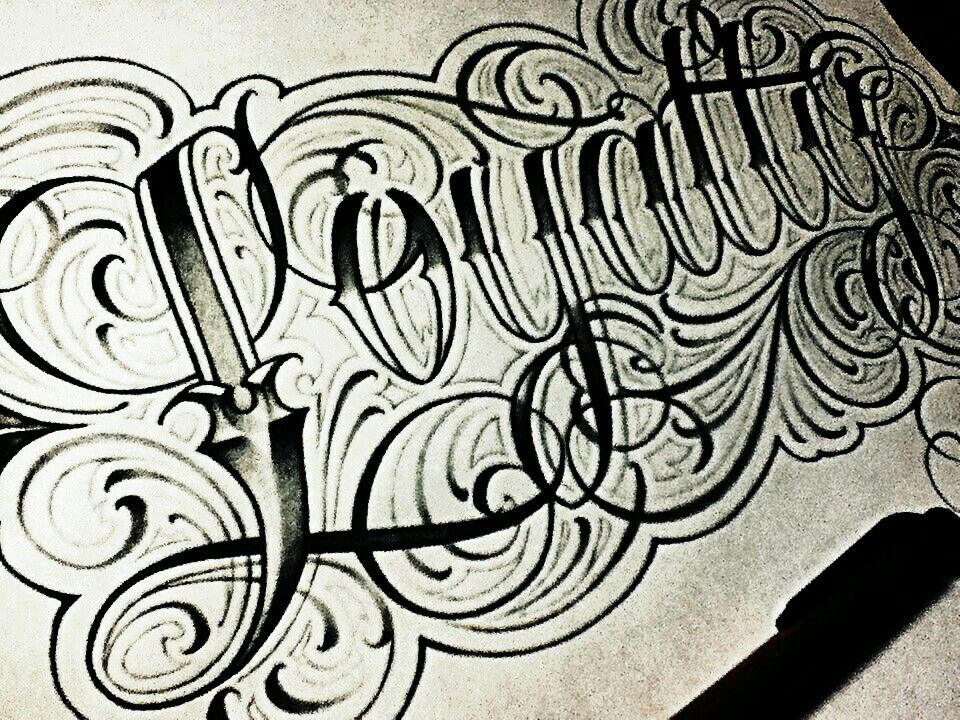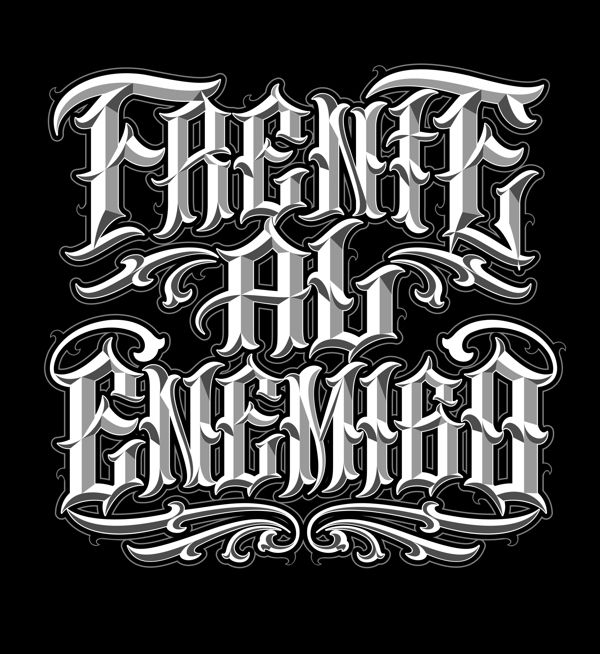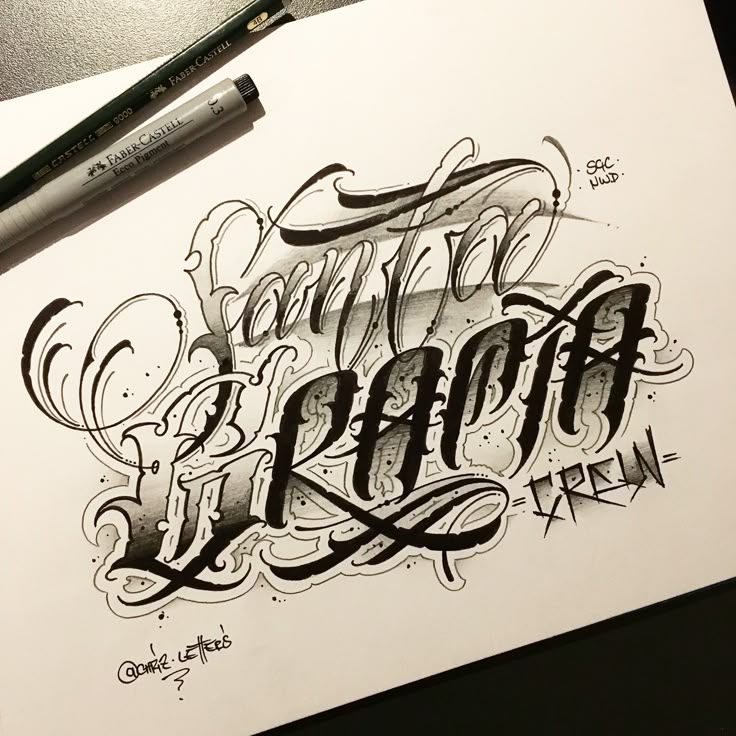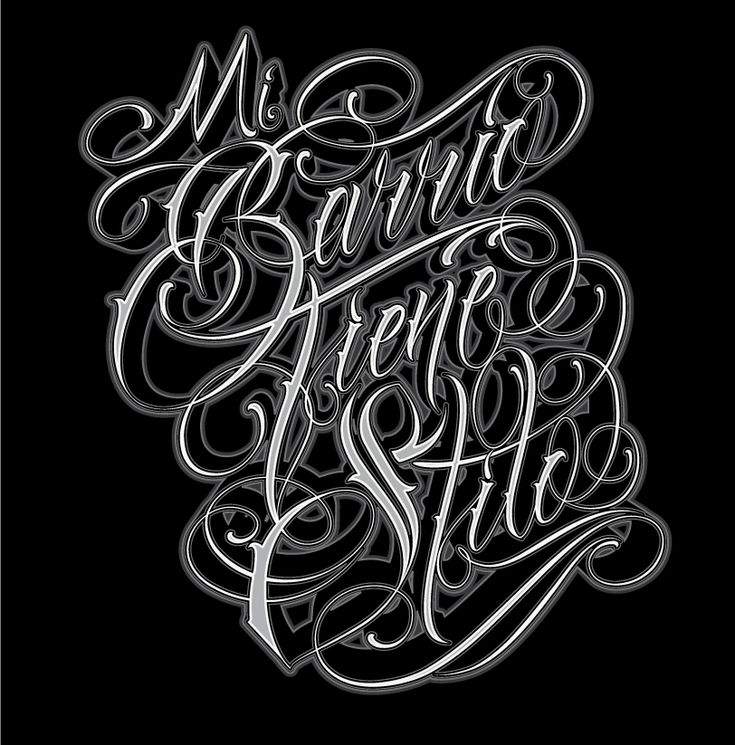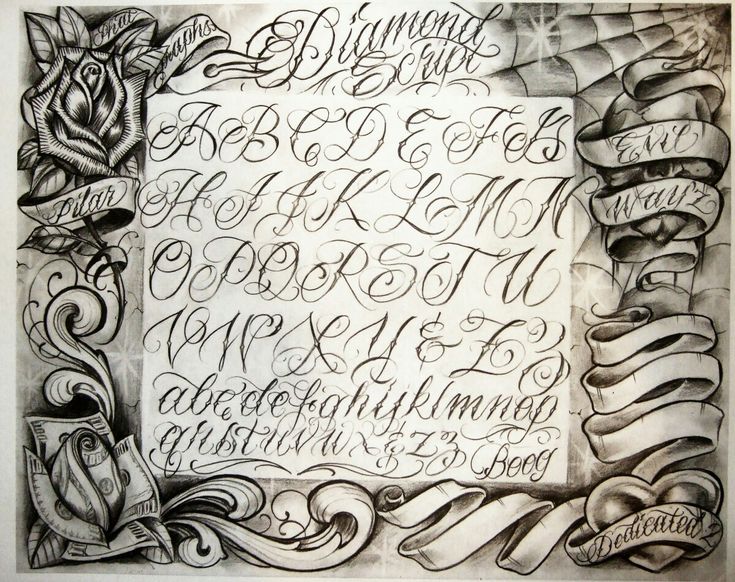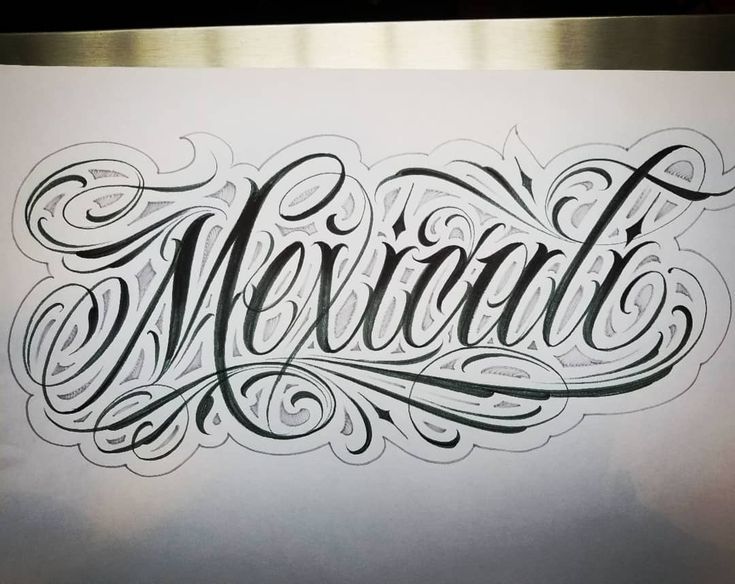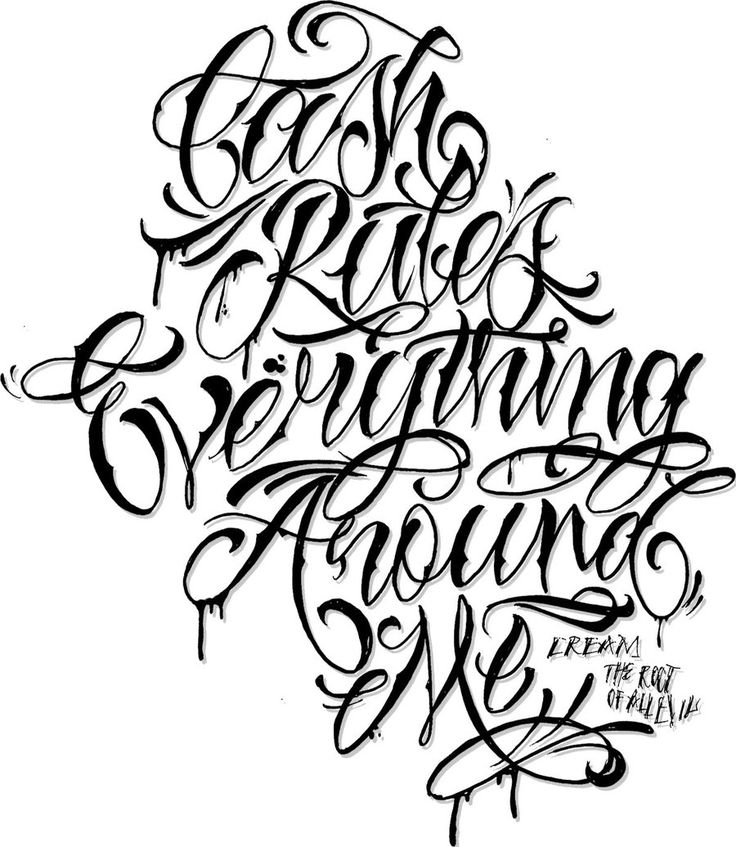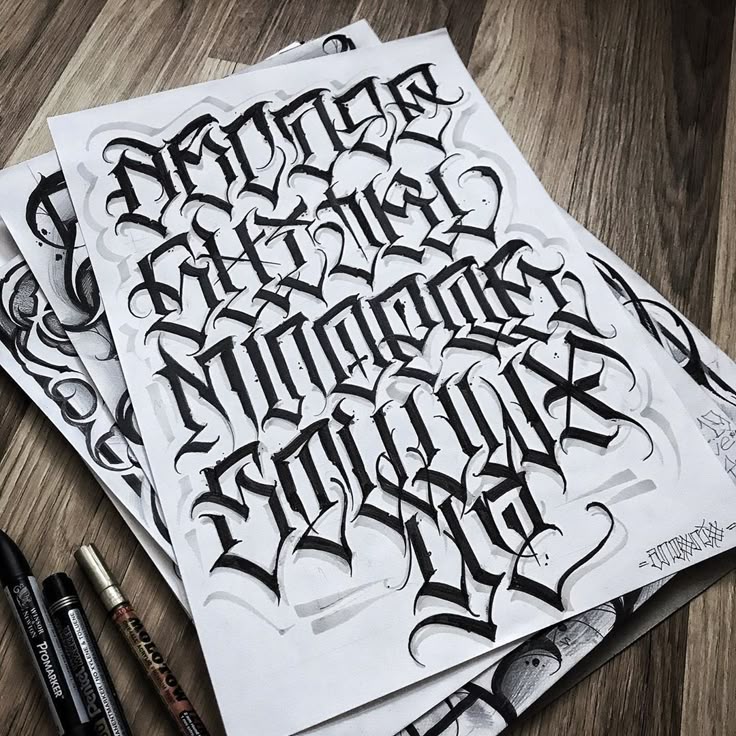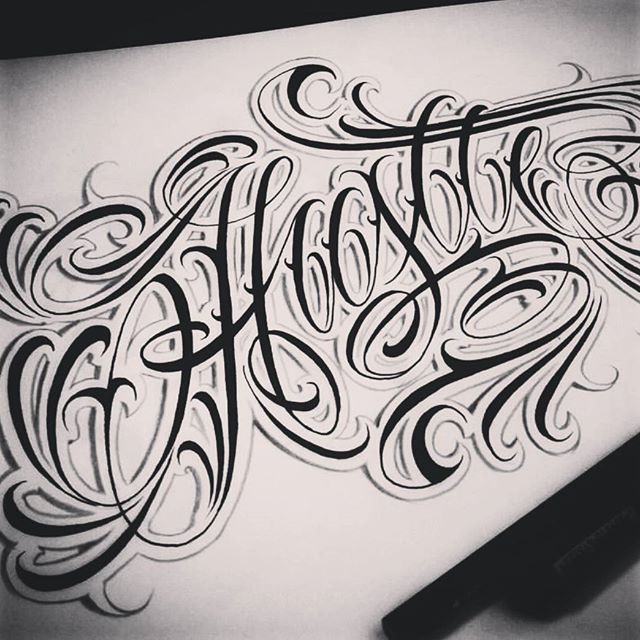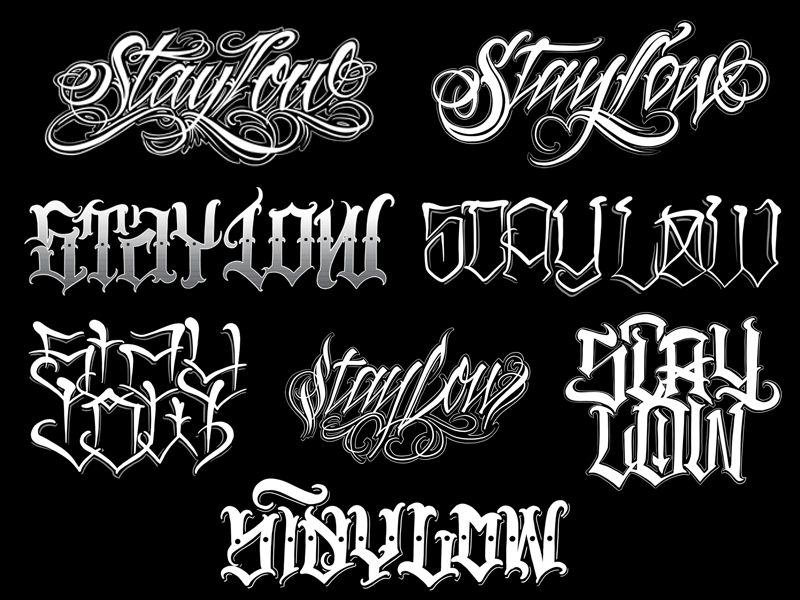
Тату надписи становятся более модными и популярными в наши дни. Их востребованность объясняется тем, что все больше людей по всему миру выбирают в качестве татуировки не простой рисунок, а текст с глубоким смыслом. Текстовые фразы могут представлять собой важные слова, имена, короткие цитаты или афоризмы, позволяющие продемонстрировать окружающим людям свои взгляды на жизнь. В статье подскажем, какой шрифт для тату можно выбрать парню или девушке, а также, рассмотрим красивые виды надписей в различных стилях.
Как подобрать шрифт для тату?
Подбор шрифтов для тату – долгое и нелегкое занятие. Вообще, в интернете существует множество сайтов и программ, позволяющих подбирать шрифты для тату надписей online.
Однако, если вы не хотите встретить другого человека с таким же красивым шрифтом, советуем вам обратиться к мастеру, который разработает стили тату надписей специально для вас. Конечно, за эту услугу придется доплатить, но в итоге, вы получите неповторимые красивые буквы, которые больше ни у кого не найдете.
В целом, девушкам больше приходятся по душе витиеватые, тонкие и изгибистые линии письма, которые часто украшаются дополнительными элементами: звездами, бабочками, цветами и пр. В то время как мужчины отдают свой выбор в пользу жирных, черных и толстых букв.
Отметим то, что отдельное внимание стоит уделить не столько внешнему виду надписи, сколько правильно подобранному интервалу между буквами. Ведь в том случае, если мастер нанесет маленькие буквы близко друг к другу, надпись со временем превратиться в нечитаемый партак, который нужно будет удалять лазером или перебивать каким-либо рисунком.
Виды шрифтов для тату
Вы хорошо подумали и решили, что хотите сделать тату надпись на своем теле.
Следующий важный шаг, который необходимо совершить – это решить, какой тату шрифт вы бы хотели использовать для своего текста. Поскольку никто бы не хотел, чтобы татуировка выглядела скучно и непривлекательно, следует провести некоторое исследование и выбрать тот шрифт тату, который придаст вам больше красоты и индивидуальности.
Самые популярные шрифты для татуировки – это латинские, кельтские, английские и русские буквы. Именно они впечатляют большинство любителей боди-арта, поскольку выглядят индивидуально и уникально. Древнеанглийские шрифты также часто используются в татуировках, потому что они имеют утонченный вид и создают атмосферу средневековья. Другие красивые варианты стилей включают в себя граффити, каллиграфию, чикано, минимализм, готику, печатный алфавит и пр.
Латинский шрифт
Латинские буквы отличаются ясностью и геометрической простотой форм. Именно поэтому латынь является одним из самых распространенных стилей в искусстве боди-арта. Латинский алфавит выбирают многие девушки, нанося татушки на свои запястья.
Готический шрифт
Буквы для тату в готической письменности отличаются надломленными жирными линии и закруглениями, выглядящими как остроконечный миндаль. В основном этот шрифт татуировки выбирают представители сильной половины человечества. Чаще всего надписи в готическом стиле наносят на предплечья, реже – на грудь.
Кельтский шрифт
Кельтский стиль письма был сформирован приблизительно в 6-7 веке после введения христианства в Ирландии. Именно в это время монахи стали писать о Евангелии. Пример написания кельтских букв имеет свои характерные особенности. В начале текста изображается большая и украшенная заглавная буква, после которой наносится текст обычного размера. Еще одна особенность написания в кельтском стиле – использование треугольных фигур в верхней части букв.
Граффити
В наше время граффити считается незаконным уличным искусством во многих странах. Но страной, которая относится к граффити с большой любовью, является Бразилия (город Сан-Паулу).
Именно он считается нынешним центром вдохновения для граффити-художников. Граффити может иметь разные стили. Обычно этот шрифт имеет два или три цвета и выполняется в виде объемных букв с жирным контуром.
Образцы разных стилей для тату надписей
Ниже продемонстрированы самые красивые стили для татуировок в виде надписей. Надеемся, что представленная подборка поможет вам определиться с видом будущей tattoo.
Тату буквы: эскизы
У каждого мастера, работающего в салоне, имеется портфолио, которое он может предоставить своему клиенту. С помощью него можно быстро произвести подбор тату шрифта и свести длительный процесс поисков к минимуму. Но если вы хотите сделать выбор самостоятельно, предлагаем ознакомиться с подборкой эскизов, представленной ниже.